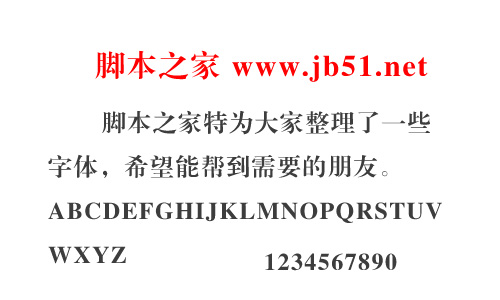
方正小标宋简体字体
方正小标宋简体字体是方正字体库中的一种字体,方正小标宋源自1964年上海印刷技术研究所设计的标题宋,是专门针对小字号标题设计的,长期被广泛用于“红头文件”的标题。相对于方正大标宋,方正小标宋的笔画略细,中宫略为放松,笔画饱满平和,字形端庄稳重,适用于人文类的文字标题。喜欢的朋友们可以前来下载使用。